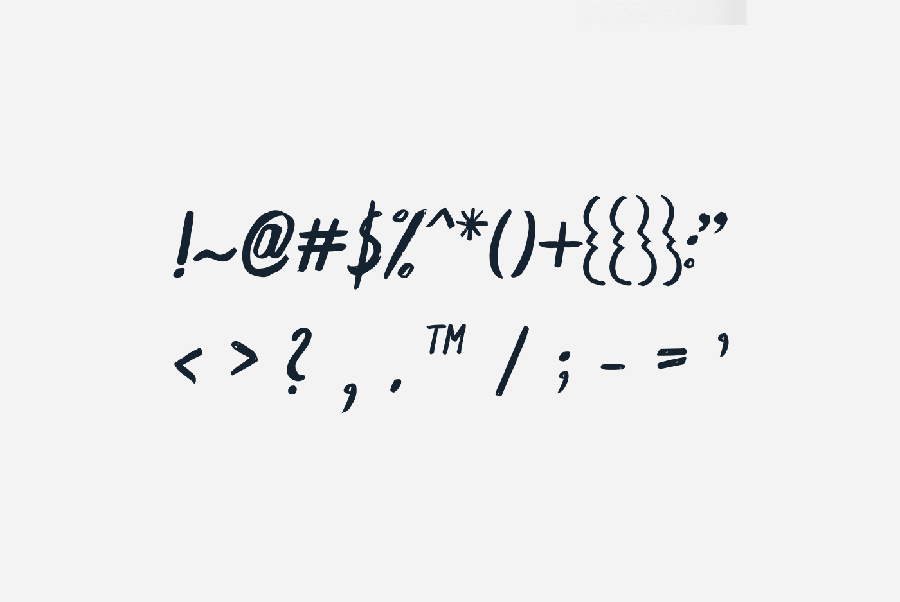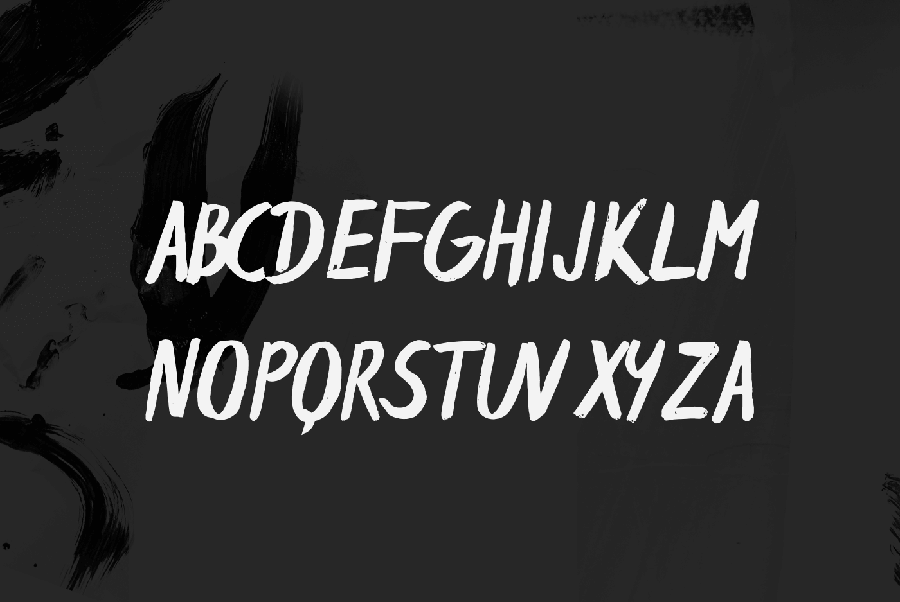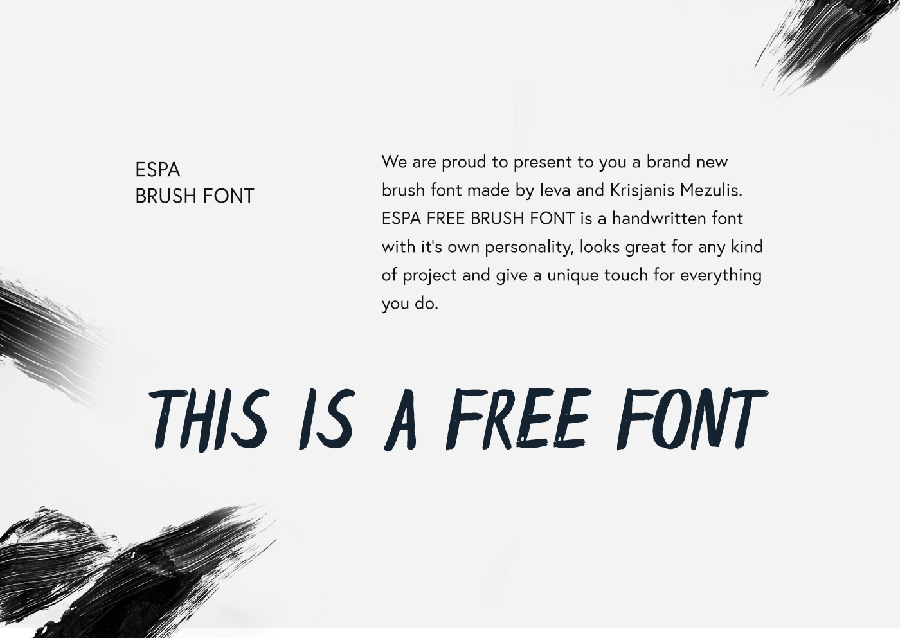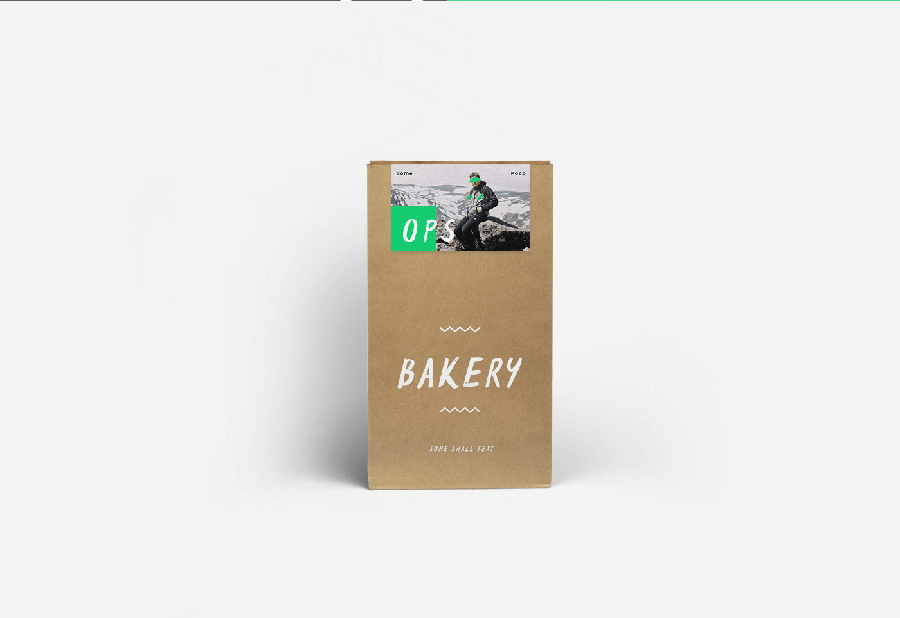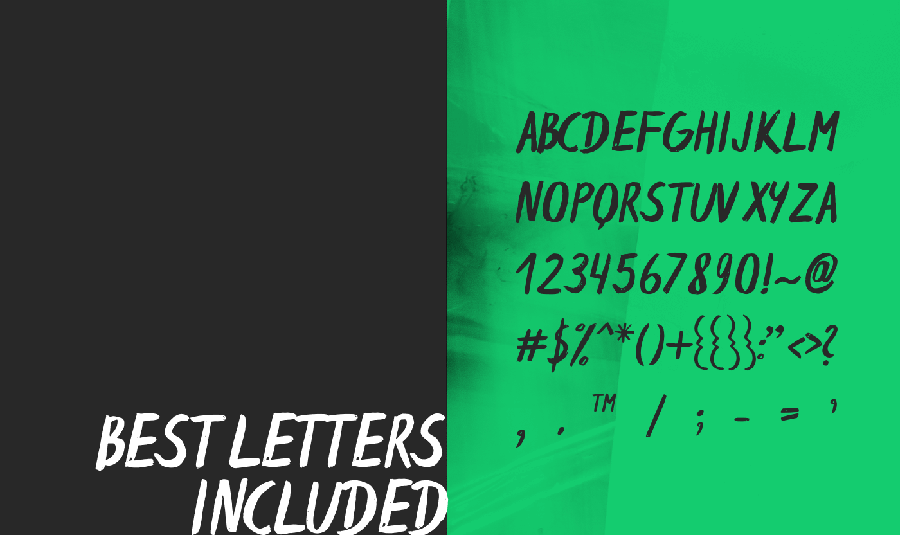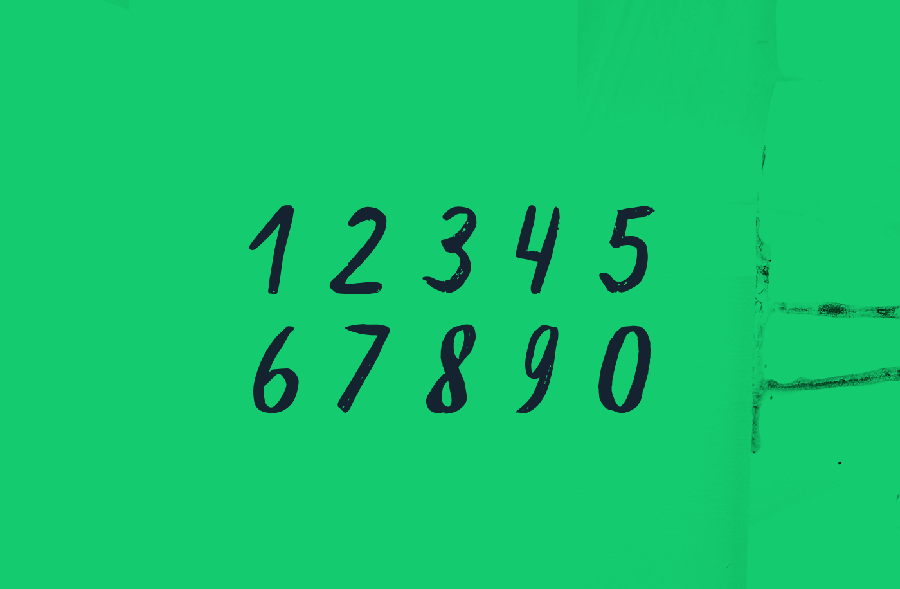
Espa刷免费字体
Espa Brush Free字体是由Ieva和Krisjanis Mezulis制作的字体。它具有刷子的感觉和外观。字体适合最好的大标题,并给他们一个个人的触摸。由于它具有自然流畅和干燥的笔触,这种字体也非常适合标志,海报和其他显示目的!这个免费版本包含92个字符,并具有所有的基本字形,.otf和.woff .woff2文件。